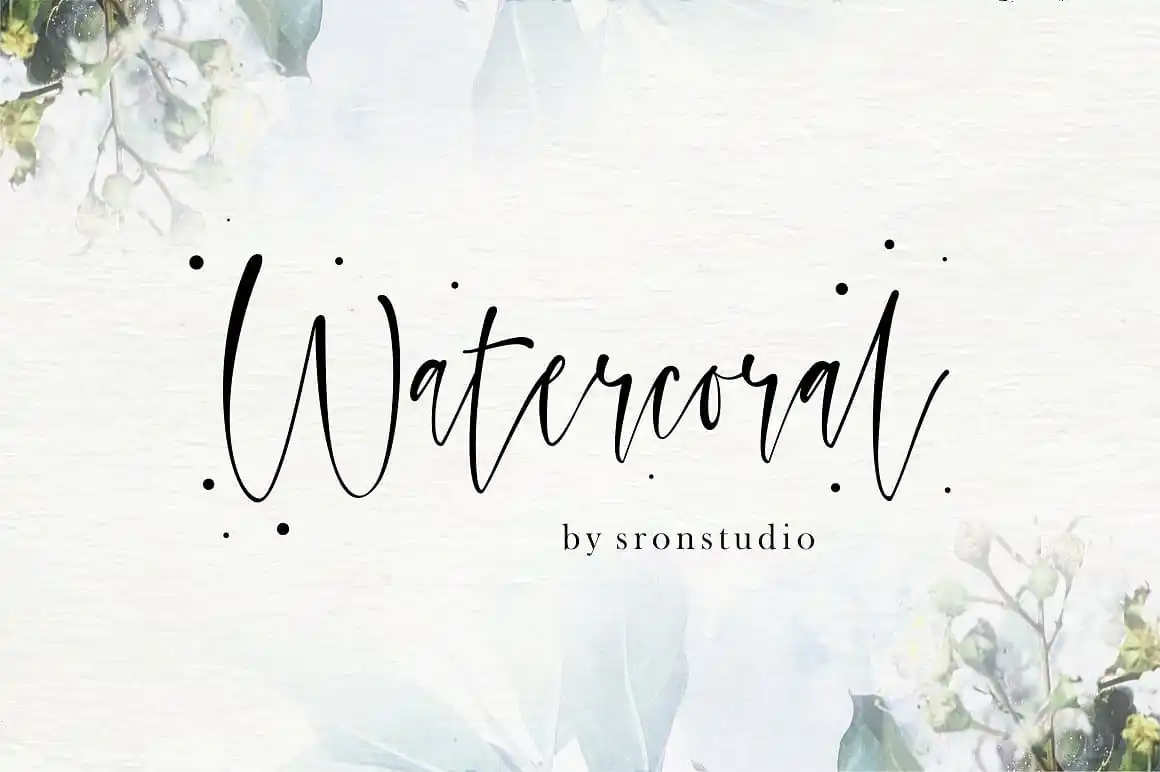
Watercoral Natural Script Font – Download Grátis
Bem-vindo ao mundo das fontes de texto natural! Hoje, apresentamos a você a Watercoral Natural Script Font, uma opção para aqueles que buscam um toque artístico e natural em seus projetos digitais. Esta fonte foi criada para designers que valorizam a arte manual. Ela se destaca especialmente nos designs de ilustração de águacolor, mas também é perfeita para qualquer projeto que exija efeitos de escrita à mão. Não confunda essa fonte somente com o design de desenho aquarelado; seu uso é extremamente versátil. A Watercoral Natural Script Font foi cuidadosamente projetada para oferecer um uso simplificado e intuitivo, sem a necessidade excessiva de alternativas. Isto facilita o uso para designers menos experientes em softwares de design, mas também para todos aqueles que desejam aplicar este charme à mão no seu próximo projeto. Seja você um artista digital ou simplesmente alguém interessado em adicionar uma pitada única a seus projetos, esta fonte é perfeita para você. Com certeza, essa font será a escolha ideal para designers buscando trazer vida e personalidade aos seus designs digitais, sem comprometer o aspecto natural de sua proposta.